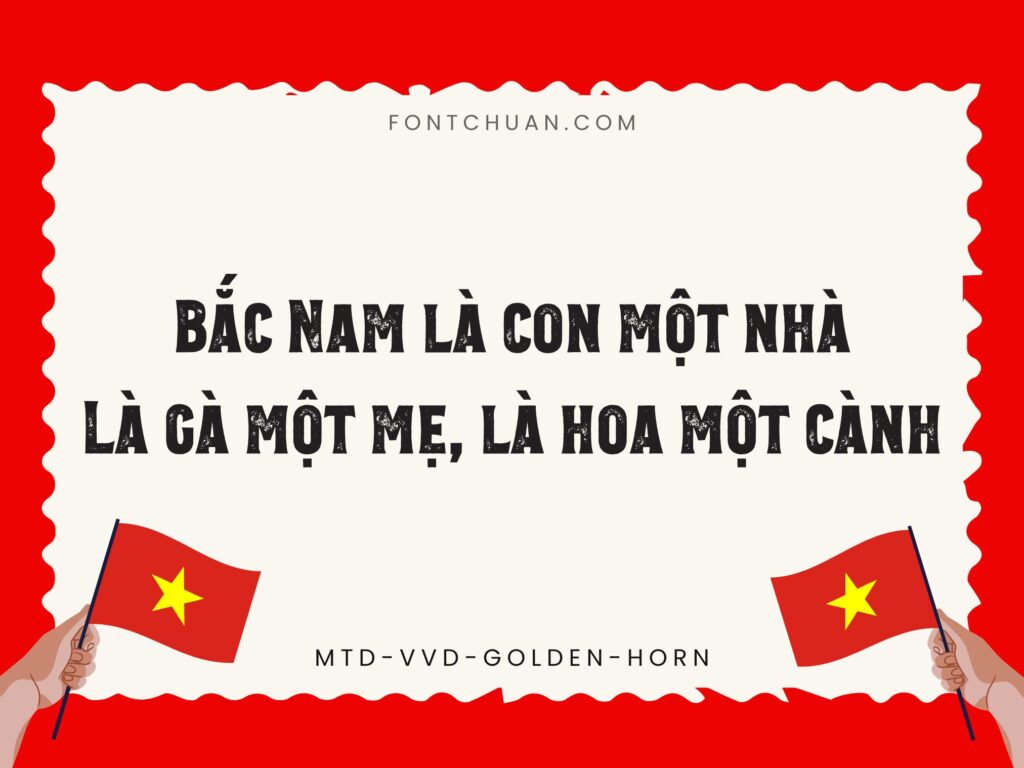
Font MTD VVD Golden Horn là một kiểu chữ sans-serif hiện đại, được thiết kế bởi Pavel Korzhenko và đã được Việt hóa bởi Mộc Hạ. Font này hỗ trợ đầy đủ tiếng Việt cùng hơn 90 ngôn ngữ khác, mở rộng khả năng ứng dụng trong các thiết kế đa ngôn ngữ. Đây là một trong những phông chữ được cộng đồng thiết kế đánh giá cao và sử dụng trong nhiều dự án sáng tạo, đáp ứng nhu cầu đa dạng của người dùng.
MTD VVD Golden Horn nổi bật với các ký tự in hoa đậm nét và mạnh mẽ, tạo cảm giác hiện đại và chuyên nghiệp. Font rất phù hợp cho các thiết kế logo, tiêu đề, bao bì sản phẩm, áp phích và các ấn phẩm đòi hỏi sự nổi bật và thu hút. Các ngành nghề phù hợp bao gồm quảng cáo, giáo dục và công nghệ. Font này cũng lý tưởng cho các sự kiện như Tết, Giáng sinh, Valentine và các lễ hội khác.